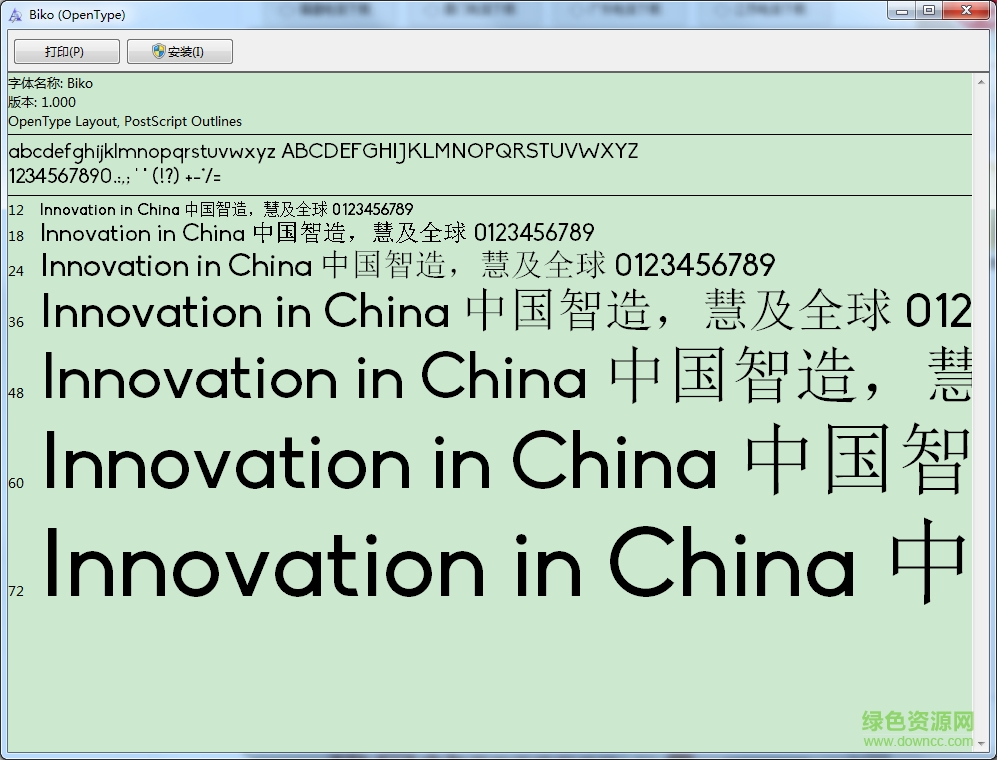
biko字體
biko是一款深受設(shè)計(jì)者喜愛的英文直字體,該字體字型結(jié)構(gòu)簡(jiǎn)潔,易讀性強(qiáng),擁有完整的字體,廣泛的應(yīng)用于平面設(shè)計(jì)、排版印刷、名片設(shè)計(jì)、廣告設(shè)計(jì)等領(lǐng)域,喜歡的朋友歡迎來綠色資源網(wǎng)下載!